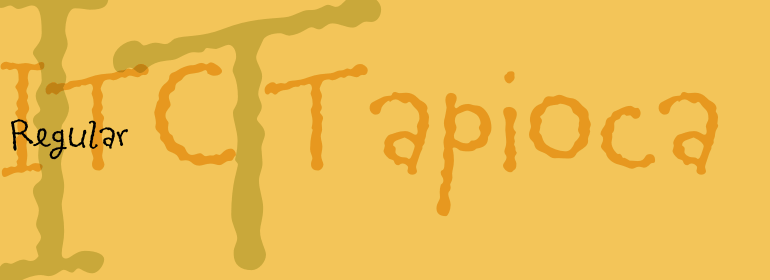
ITC Tapioca™
ITC Tapioca™,这款字体结构工整、笔画清晰,兼顾美观与易读性,适用于标题、正文、海报、包装、LOGO 等多种场景。字形优雅稳定,风格百搭耐看,适配日常排版与创意设计,让文字呈现更舒适、更具质感。ITC Tapioca™一笔一画,皆是细节,以均衡的比例、流畅的线条打造舒适视觉体验,字形端正大气,风格简约现代。无论是商业设计、品牌宣传还是日常排版,都能轻松驾驭,让文字更有格调与力量。ITC Tapioca™字体下载。
ITC Tapioca由Eric Stevens设计。他为一家夜总会设计了这种字体,但它的简单形式让人想起童年时代的写作练习。粗糙的边缘增强了这种效果,这使得字符在大尺寸显示时看起来像是由一长串的点……或是木薯粉组成。虽然某些形式采用了草书手写形式,但基本样式还是印刷手写体。字符不同的倾斜角度和不规则的形状使ITC Tapioca充满了活力和趣味性。
ITC Tapioca was designed by Eric Stevens. He developed the typeface for a nightclub, yet its simple forms are reminiscent of childhood writing exercises. This effect is enhanced by rough edges, which in large sizes make the characters look as though they were composed of strings of dots...or tapioca. The basic style is printed handwriting, although some forms take cursive handwritten forms. The varying slants and irregular forms of the characters give ITC Tapioca a sense of energy and playfulness.